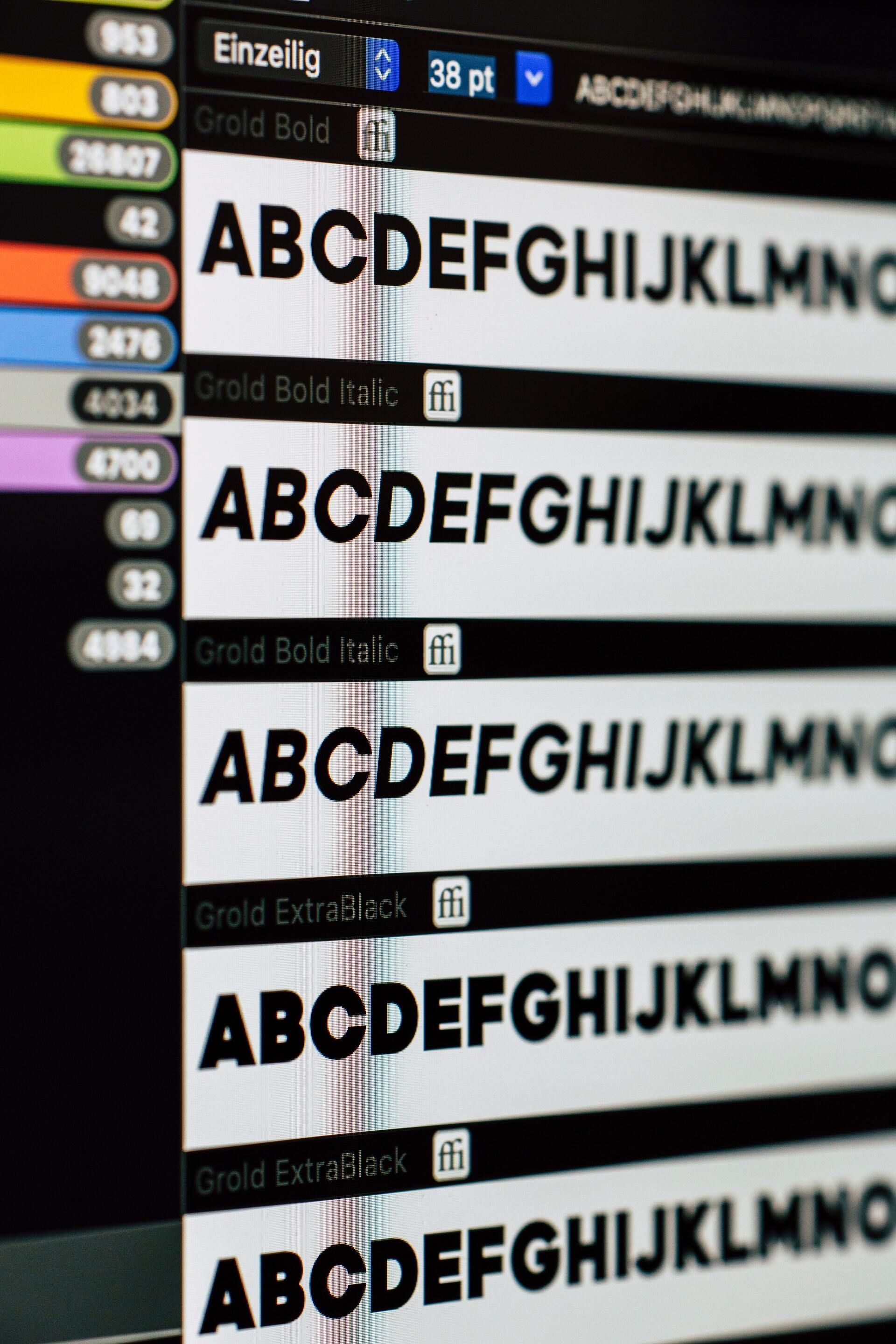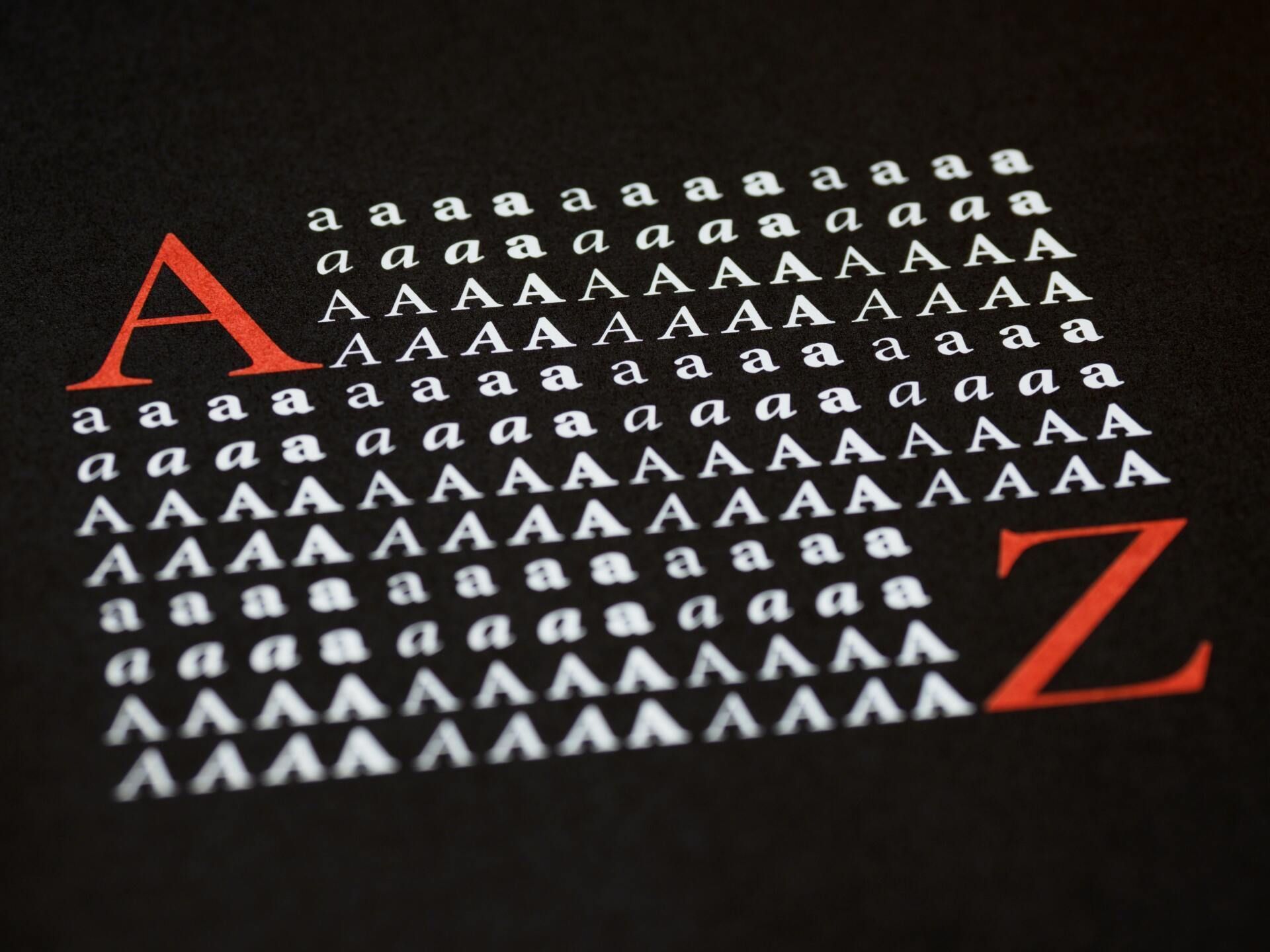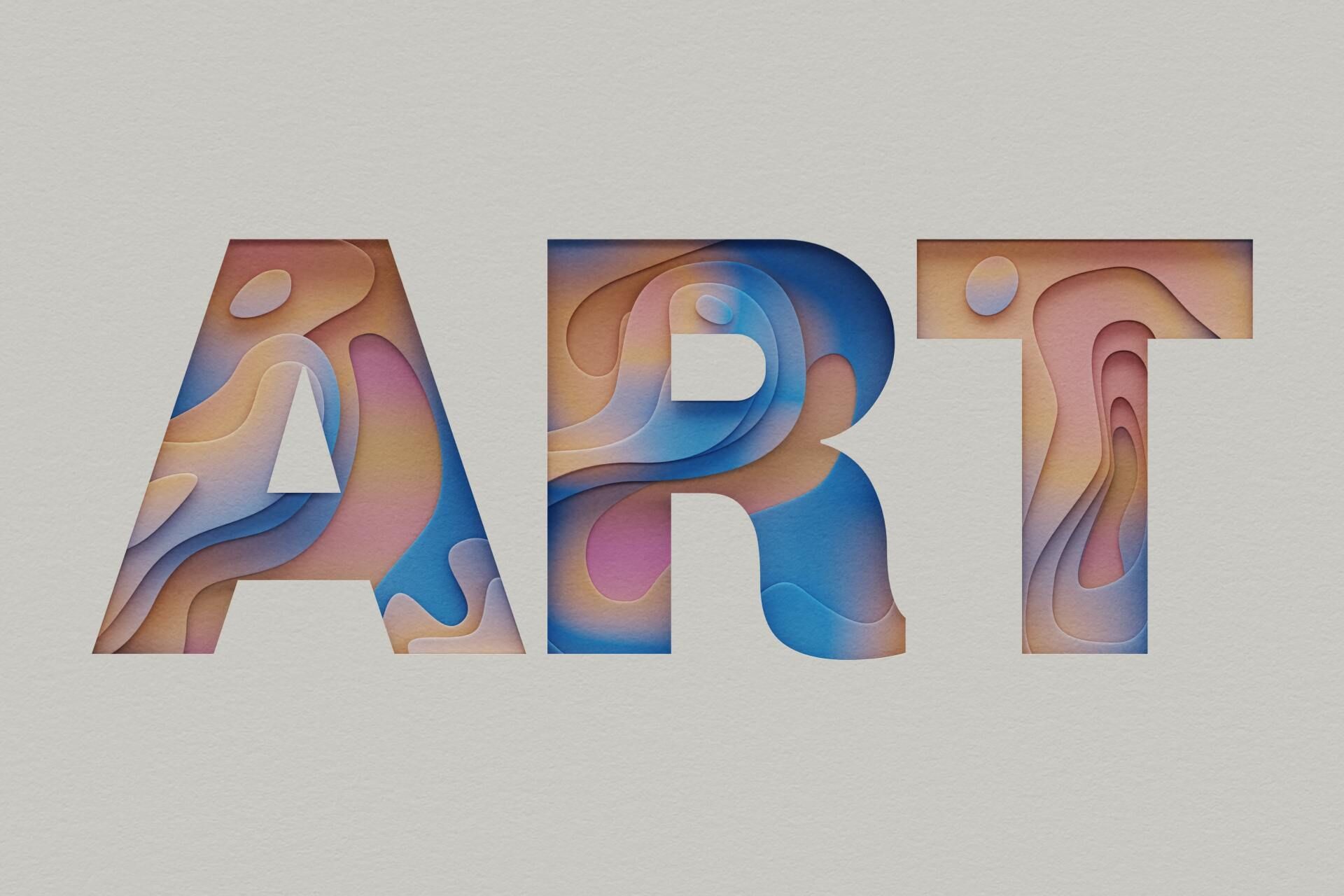
La importancia de la tipografía en tus anuncios publicitarios
La tipografía es el arte de ordenar las letras y el texto de manera que el copy sea legible, claro y visualmente atractiva para el lector.
La tipografía implica estilo de fuente, apariencia y estructura, cuyo objetivo es provocar ciertas emociones y transmitir mensajes específicos. En resumen, la tipografía es lo que da vida al texto.
En este artículo queremos explicar por qué la tipografía es importante y qué diferencia hace para tus usuarios y seguidores.
El primer ejemplo de tipografía se puede ver en la Biblia de Gutenberg, que inició una revolución tipográfica en Occidente.
Volviendo a la actualidad, la tipografía se asocia principalmente con el mundo digital y la impresión . Con el nacimiento de Internet llegó una explosión creativa del arte de la tipografía.
De repente, los diseñadores web tienen a su alcance una gran cantidad de fuentes y opciones de tipografía a su disposición , lo que hizo que la tipografía fuera más diversa visualmente que nunca.
La tipografía es mucho más que elegir fuentes hermosas, es un componente vital del diseño de la interfaz y experiencia del usuario.
Una buena tipografía establecerá una fuerte jerarquía visual, proporcionará un equilibrio gráfico al sitio web y establecerá el tono general del producto.
En este artículo queremos explicar por qué la tipografía es importante y qué diferencia hace para tus usuarios y seguidores.
Significado e importancia de la tipografía
La tipografía se remonta al siglo XI, durante la invención de la imprenta. Antes de la era digital, la tipografía era un oficio especializado asociado con libros y revistas y, finalmente, con obras públicas.El primer ejemplo de tipografía se puede ver en la Biblia de Gutenberg, que inició una revolución tipográfica en Occidente.
Volviendo a la actualidad, la tipografía se asocia principalmente con el mundo digital y la impresión . Con el nacimiento de Internet llegó una explosión creativa del arte de la tipografía.
De repente, los diseñadores web tienen a su alcance una gran cantidad de fuentes y opciones de tipografía a su disposición , lo que hizo que la tipografía fuera más diversa visualmente que nunca.
La tipografía es mucho más que elegir fuentes hermosas, es un componente vital del diseño de la interfaz y experiencia del usuario.
Una buena tipografía establecerá una fuerte jerarquía visual, proporcionará un equilibrio gráfico al sitio web y establecerá el tono general del producto.
Características de la tipografía
La tipografía genera reconocimiento de marca
Una buena tipografía no solo mejorará la personalidad del sitio web o anuncios publicitarios impresos , sino que tus usuarios comenzarán a asociar subliminalmente el tipo de letra que aparece en su sitio con tu marca.
La tipografía única y consistente te ayudará a establecer un fuerte seguimiento de atracción de usuarios, generar confianza con tus clientes y ayudar a llevar tu marca hacia adelante.
La tipografía influye en la toma de decisiones
La tipografía tiene un efecto profundo en la forma en que los usuarios digieren y perciben la información que transmite el texto.
El tipo llamativo es mucho más persuasivo que las fuentes débiles que no refuerzan el mensaje del texto.
La tipografía mantiene la atención de los lectores
Una buena tipografía podría ser
la diferencia entre que alguien permanezca en tu sitio web durante un minuto o media hora. Es importante que tu sitio web sea visualmente estimulante y memorable, y la tipografía juega un papel muy importante en este proceso.
Los efectos de la tipografía
Para comenzar con la tipografía, primero debes familiarizarte con los
seis elementos de diseño tipográfico
esenciales que tienen una incidencia directa en el efecto que ocasionan.
Existe cierta confusión en torno a la diferencia entre tipos de letra y fuentes, y muchos los tratan como sinónimos.
Un tipo de letra es un estilo de diseño que comprende una infinidad de caracteres de diferentes tamaños y pesos, mientras que una fuente es una representación gráfica del carácter del texto.
En pocas palabras, un tipo de letra es una familia de fuentes relacionadas, mientras que las fuentes se refieren a los pesos, anchos y estilos que constituyen un tipo de letra.
Al igual que la jerarquía, el contraste ayuda a transmitir qué ideas o mensajes deseas enfatizar a tus lectores.
Dedicar algo de tiempo al contraste hace que tu texto sea interesante, significativo y llamativo.
Mantener la
consistencia de los tipos de letra
es clave para evitar una interfaz confusa y desordenada.
Al transmitir información, es esencial mantener el mismo estilo de fuente, para que tus lectores comprendan instantáneamente lo que están leyendo y comiencen a notar un patrón.
Aunque está bien jugar con los niveles de jerarquía hasta cierto punto, es una buena práctica establecer una jerarquía consistente de tipos de letra (una fuente consistente para los encabezados, otra para los subtítulos) y ceñirse a ella.
A menudo denominado "espacio negativo", el espacio en blanco es el espacio alrededor del texto o los gráficos.
Comúnmente se pasa por alto y tiende a pasar desapercibido para el usuario, pero el uso adecuado de los espacios en blanco garantiza que la interfaz esté despejada y que el texto sea legible.
Los espacios en blanco suelen adoptar la forma de márgenes, relleno o simplemente áreas sin texto ni gráficos.
Alineación
La alineación es el proceso de unificar y combinar texto, gráficos e imágenes para garantizar que haya el mismo espacio, tamaño y distancia entre cada elemento.
Muchos diseñadores crean márgenes para garantizar que el logotipo, encabezado y cuerpo del texto estén alineados entre sí.
Por ejemplo, alinear el texto a la derecha parecerá contradictorio para los lectores que leen de izquierda a derecha.
Color
El color es uno de los elementos más emocionantes de la tipografía. Aquí es donde los diseñadores pueden ser realmente creativos y elevar la interfaz a un nuevo nivel.
Sin embargo, el color del texto no debe tomarse a la ligera: clavar el color de la fuente puede hacer que el texto se destaque y transmita el tono del mensaje. Hacerlo mal puede resultar en una interfaz desordenada y un texto que choca con los colores del sitio.
El color tiene tres componentes clave: valor, matiz y saturación. Un buen diseñador sabrá cómo equilibrar estos tres componentes para que el texto sea llamativo y claramente legible, incluso para personas con discapacidades visuales.
A menudo, los diseñadores probarán esto viendo el texto en escala de grises (sin color) y haciendo ajustes si el texto es demasiado oscuro o demasiado claro contra el color de fondo.
Establecer una jerarquía es uno de los principios más vitales de la tipografía . La jerarquía tipográfica tiene como objetivo crear una distinción clara entre las piezas destacadas del copy que deben notarse y leerse primero.
En una era de períodos de atención cortos provocados por las redes sociales, se insta a los diseñadores a ser concisos y crear tipos de letra que permitan a los usuarios consumir la información necesaria en períodos cortos de tiempo.
Es por ello que en Geformas no solo te ofrecemos múltiples opciones de impresión, sino también un diseño impecable realizado por expertos.
Fuentes y tipos de letra
Existe cierta confusión en torno a la diferencia entre tipos de letra y fuentes, y muchos los tratan como sinónimos.
Un tipo de letra es un estilo de diseño que comprende una infinidad de caracteres de diferentes tamaños y pesos, mientras que una fuente es una representación gráfica del carácter del texto.
En pocas palabras, un tipo de letra es una familia de fuentes relacionadas, mientras que las fuentes se refieren a los pesos, anchos y estilos que constituyen un tipo de letra.
Contraste
Al igual que la jerarquía, el contraste ayuda a transmitir qué ideas o mensajes deseas enfatizar a tus lectores.
Dedicar algo de tiempo al contraste hace que tu texto sea interesante, significativo y llamativo.
Consistencia
Mantener la
consistencia de los tipos de letra
es clave para evitar una interfaz confusa y desordenada.
Al transmitir información, es esencial mantener el mismo estilo de fuente, para que tus lectores comprendan instantáneamente lo que están leyendo y comiencen a notar un patrón.
Aunque está bien jugar con los niveles de jerarquía hasta cierto punto, es una buena práctica establecer una jerarquía consistente de tipos de letra (una fuente consistente para los encabezados, otra para los subtítulos) y ceñirse a ella.
Espacio en blanco
A menudo denominado "espacio negativo", el espacio en blanco es el espacio alrededor del texto o los gráficos.
Comúnmente se pasa por alto y tiende a pasar desapercibido para el usuario, pero el uso adecuado de los espacios en blanco garantiza que la interfaz esté despejada y que el texto sea legible.
Los espacios en blanco suelen adoptar la forma de márgenes, relleno o simplemente áreas sin texto ni gráficos.
Alineación
La alineación es el proceso de unificar y combinar texto, gráficos e imágenes para garantizar que haya el mismo espacio, tamaño y distancia entre cada elemento.
Muchos diseñadores crean márgenes para garantizar que el logotipo, encabezado y cuerpo del texto estén alineados entre sí.
Por ejemplo, alinear el texto a la derecha parecerá contradictorio para los lectores que leen de izquierda a derecha.
Color
El color es uno de los elementos más emocionantes de la tipografía. Aquí es donde los diseñadores pueden ser realmente creativos y elevar la interfaz a un nuevo nivel.
Sin embargo, el color del texto no debe tomarse a la ligera: clavar el color de la fuente puede hacer que el texto se destaque y transmita el tono del mensaje. Hacerlo mal puede resultar en una interfaz desordenada y un texto que choca con los colores del sitio.
El color tiene tres componentes clave: valor, matiz y saturación. Un buen diseñador sabrá cómo equilibrar estos tres componentes para que el texto sea llamativo y claramente legible, incluso para personas con discapacidades visuales.
A menudo, los diseñadores probarán esto viendo el texto en escala de grises (sin color) y haciendo ajustes si el texto es demasiado oscuro o demasiado claro contra el color de fondo.
Establecer una jerarquía es uno de los principios más vitales de la tipografía . La jerarquía tipográfica tiene como objetivo crear una distinción clara entre las piezas destacadas del copy que deben notarse y leerse primero.
En una era de períodos de atención cortos provocados por las redes sociales, se insta a los diseñadores a ser concisos y crear tipos de letra que permitan a los usuarios consumir la información necesaria en períodos cortos de tiempo.